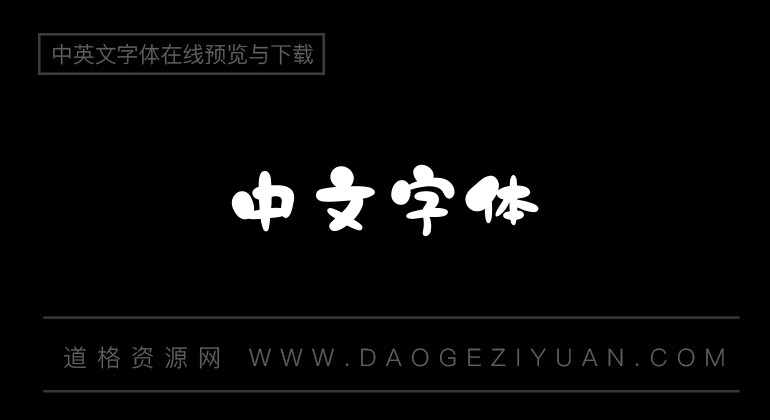
站酷彤彤体
站酷彤彤体是一款字体设计,由站酷字体设计师绘制,属于站酷独家设计字体,其特点是拥有优雅的线条,流畅的节奏,和清晰的结构,可以用于各种商业设计,如海报、画册、网页、品牌标识等。
站酷彤彤体是一款非常不错的手写艺术字体,具有很好的视觉感,适合于文化类的宣传设计、商业类品牌的广告和产品包装设计以及个性化文字排版等较多场景。
站酷彤彤体字符映射图